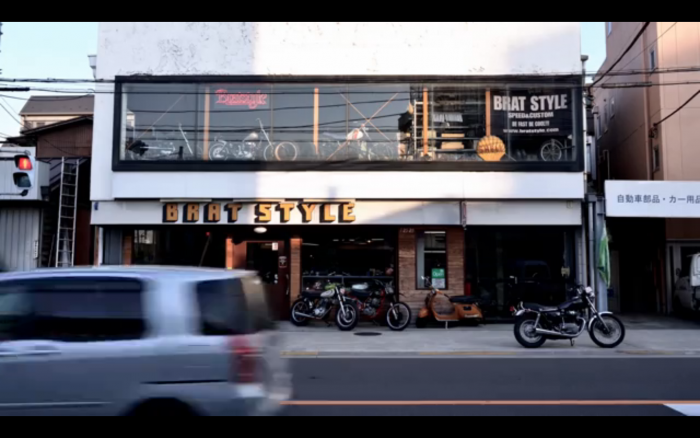
kann mir jemand sagen welche schrift das ist....?
Ist hier niemand dabei? oder vielleicht kann mir jemand eine ähnliche schrift empfehlen?
Kann gut sein, dass das einfach gemalt ist und nicht auf einem Font beruht.
Worum geht’s dir denn? Um den blockartigen Look der orangen Buchstaben? Oder eher um den 3D-Look?
Und darf die alternative Schrift was kosten?
mir geht es um den "blockigen" look und den 3d effekt... der sollte allerdings genau die selbe ausrichtung wie bei dieser schrift haben... kennst du evtl. eine ähnliche? ich hab auch schon nach einer ähnlichen schrift gesucht, habe auch eine gefunden nur leider verspringen die letter oder sind auch schon leicht gedreht um den 3d effekt zu verstärken vermute ich.
wow super... die bad mofo kommt schon hin... tausend dank!
OK DIE MOFO SIEHT SCHON FAST GUT AUS... eins stört daran leider... das sind die abgeschnittenen ecken einiger letter... und u.a. verspringt das t nach unten...
ich hätte nicht gedacht, dass die schriftart so selten ist bzw. keine wirklich gleichartige existiert oder eben so schwer zu finden ist..
wie gesagt, der font ist sicherlich angepasst wurden.
dieser ist zumindestens ähnlich.
danke! das habe ich verstanden.... wie komme ich jetzt an genau diese schrift... es mag verrückt klingen doch muss es genau diese sein... also bin  ich auch weiterhin für jede hilfe dankbar.
die, also die ich empfohlen habe?
die kannst du unter dem namen "pioneer" hier:
kaufen. wenns die andere schrift sein soll: nachbauen.
sollte nicht schwierig sein.
hehe ok danke... ich bin wie gesagt laie also könnte ich sie wohl maximal nachmalen... und danke für die pioneer.. die passt aber nicht ganz.